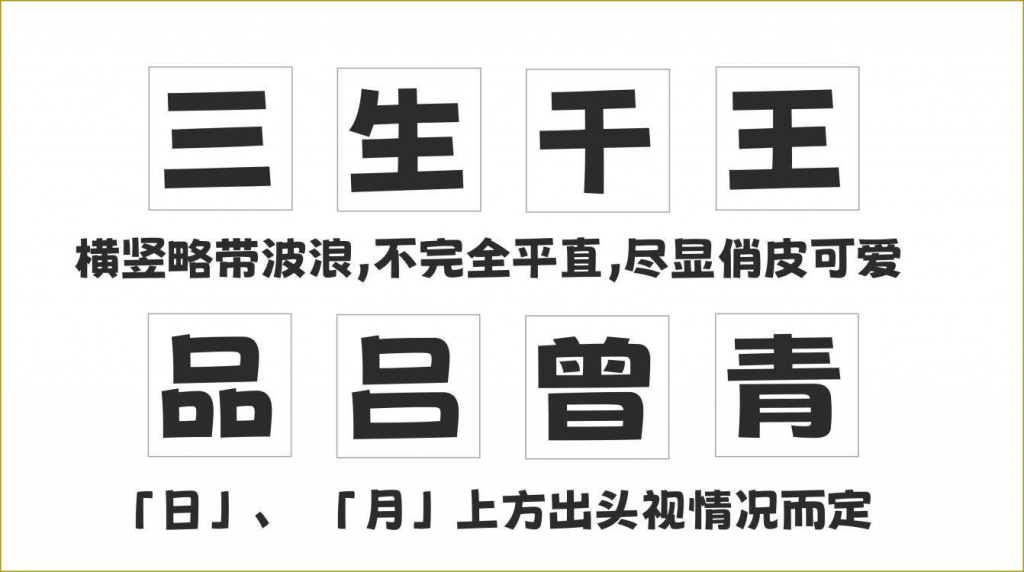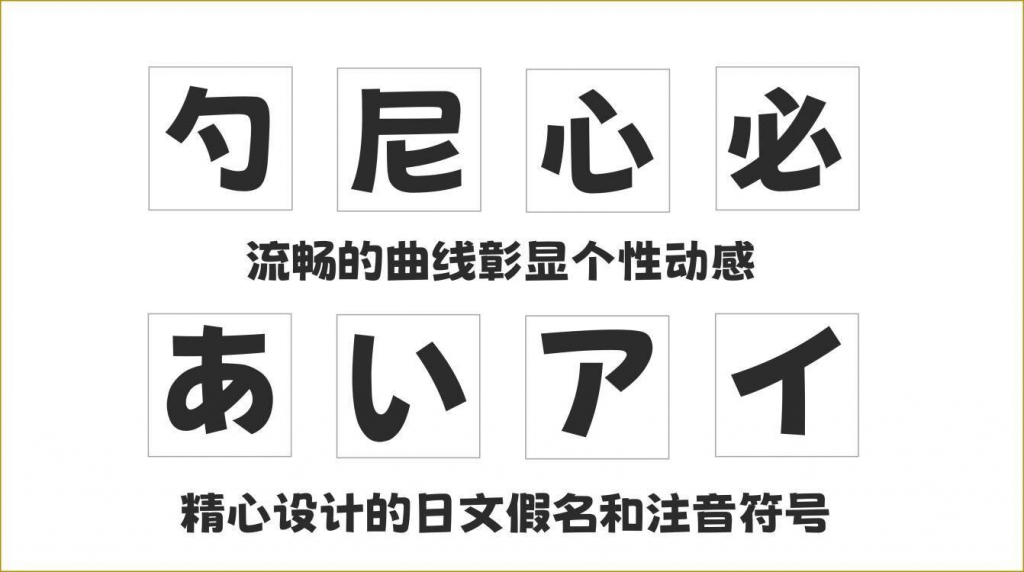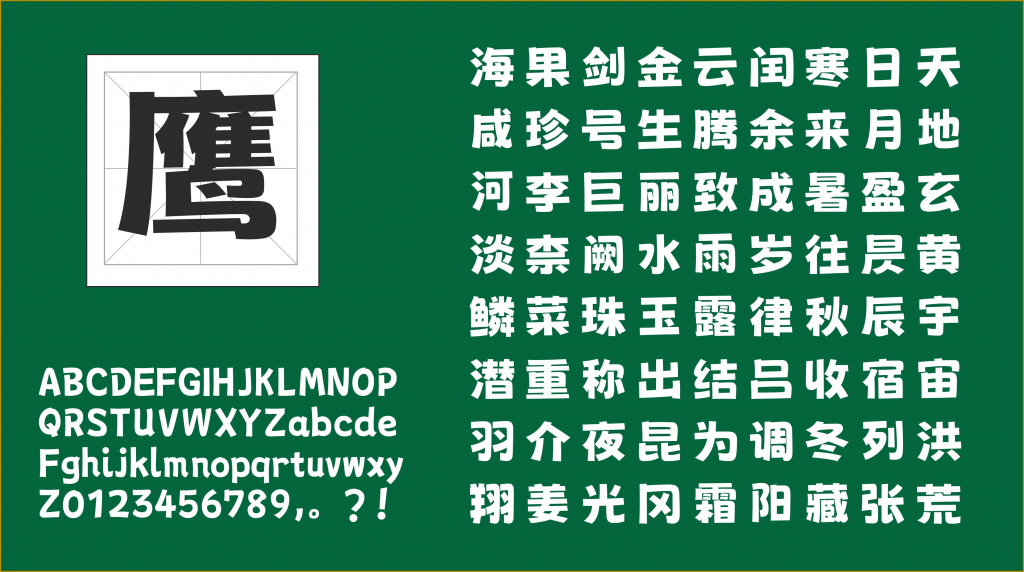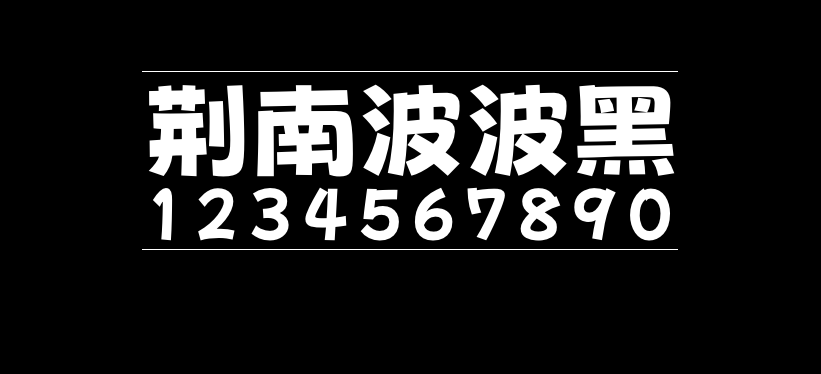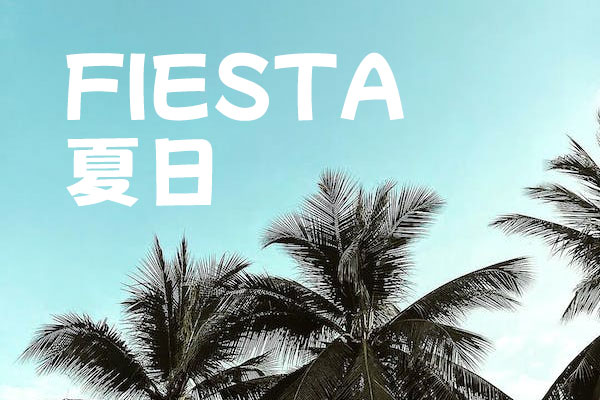
荆南波波黑
荆南波波黑是荆南字坊推出的一款卡通风格字体,该字体以OFL协议开放发布,您可以免费用于个人及商业用途。
现在的免费商用中文字体,大多以综艺体系的美术字体为主。想要找个可爱又不失实用型的标题卡通字体选择很少,几乎只能选择收费的商业字体。为了填补这个空缺,荆南字坊特将其企划已久的「波波黑」开放为免费商用字体。
荆南波波黑于2023年03月09日更新1.70版本,补全方正简繁、日文STD、部分香港常用字,并额外按需补全其他异体字,目前共收纳15905字,覆盖GB2312标准所有字符,可放心下载使用。
荆南波波黑横竖略带波浪,不完全平直,尽显俏皮可爱。
口左上角的出头视情况而定。
精心设计的日文假名和注音符号。
流畅的曲线彰显个性动感。
字体笔画粗细排布均一合理,小字可读性较高。